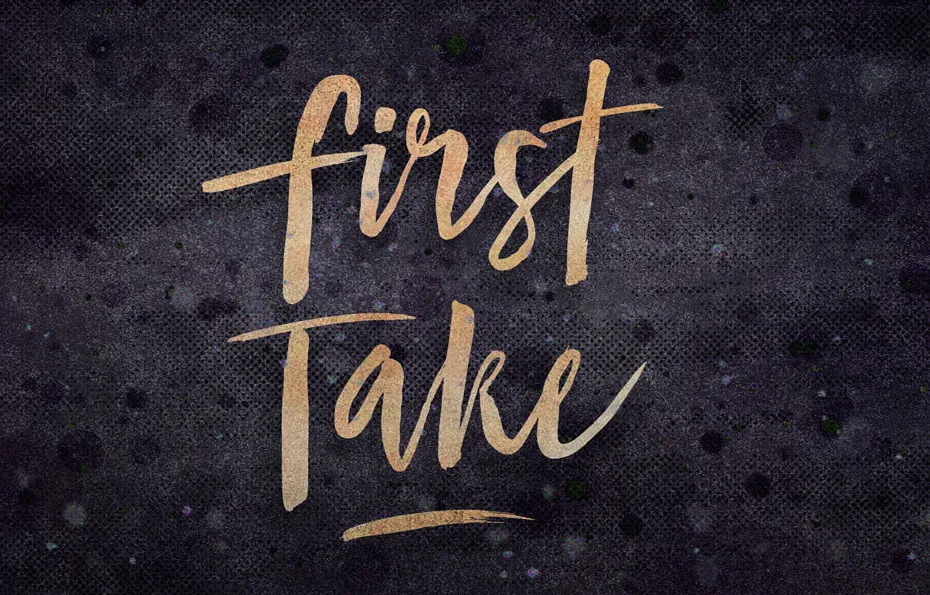
Descubra uma nova adição à coleção de fontes brush do designer 178-MC com First Take Brush Font. Este tipo de letra branco e preto foi criado a partir da paixão e habilidade do artista por letras escritas a mão, inspirando designs que refletem autenticidade e sensibilidade. Perfeito para criações como logomarcas, identidades de marca, cartões de festa, casamentos, redes sociais, layouts de revistas e muito mais, First Take Brush Font oferece uma escolha única e emocionante para personalizar seus projetos com autenticidade. Com suas imperfeições ligeiras inspiradas no processo criativo, a fonte proporciona centenas de caracteres que permitem um toque extra de autêntica letra escrita à mão em suas criações. Um presente valioso para designers e amantes do design buscando uma escolha única e emocional entre as opções disponíveis.